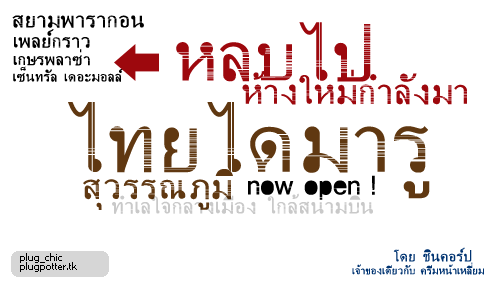
ฟอนต์เพื่อเด็กแนว PLUG_Chic
ฟอนต์ใหม่ของปลั๊กนะ อันนี้คิดอยากทำมานาน แต่พอเปิดโปรแกรมแล้วลืมทุกที
ไปทำห่วยๆ แทน 55+ อันนี้เคยเห็นในแม็กกาซีน ต่างๆ ของเมืองนอก เว็บแนว ๆ
ลองทำเป็นไทยบ้าง ใช้นายพลเทมเพลต
ฟอนต์ต้นแบบคือ เซน ซีรีฟ .. อันนี้เราเอามาทำต่อได้ใช่มั้ยอ่ะ ถ้าผิดกฎหมายยังไง
ไม่ลองวาดขึ้นมาใหม่เลยครับ ได้ทักษะ + ฝึกฝีมือไปด้วย  :05:
ปล. ฟ๐นต์สวยจะตาย
ทำโลด รอดูด  :22:
ชอบภาษาอังกฤษอ่ะ สวยกว่า   :08:
ปล่อยไปแล้วนี่ตัวนี้
ตูชอบตรงหัวตันๆ มากเลยรู้เปล่า
ดูมีรสนิยมทันสมัยดี
ชอบมาก ให้ห้าดาวไปแล้ว